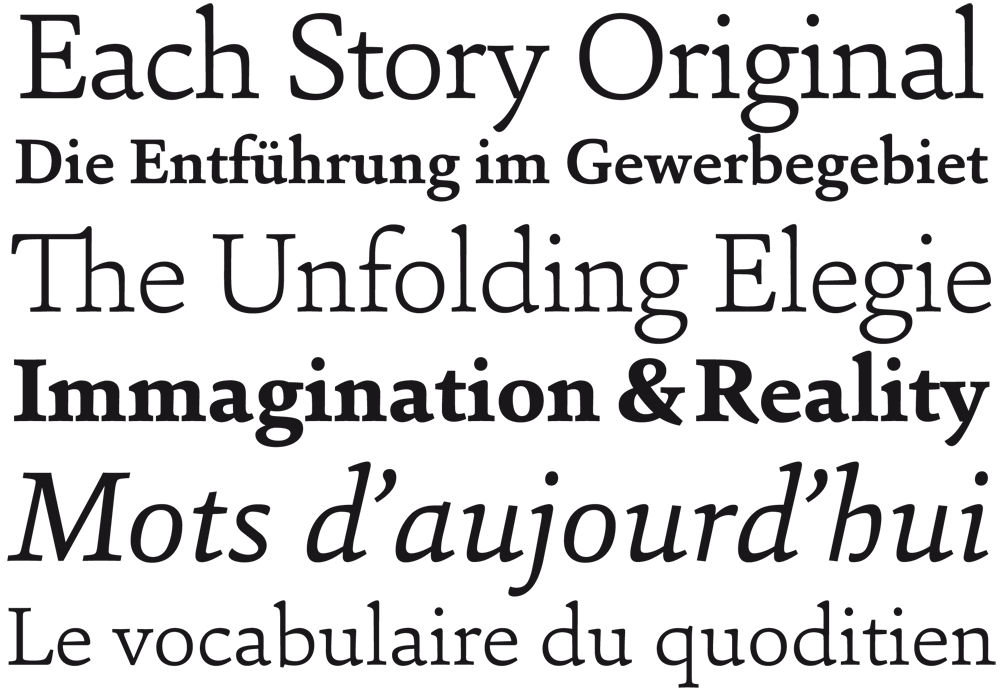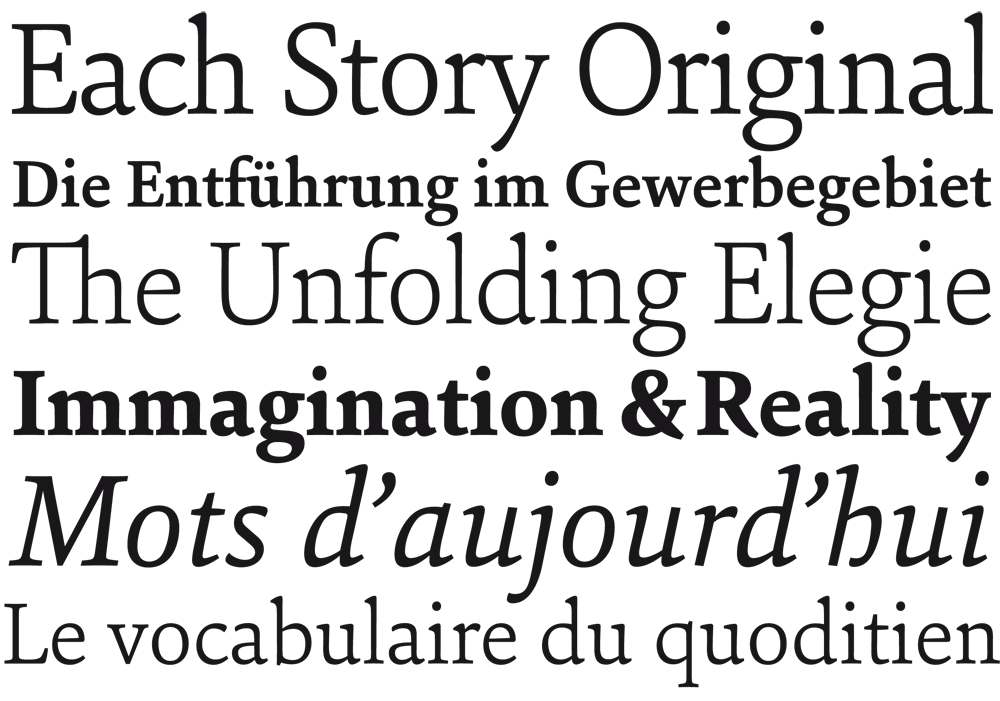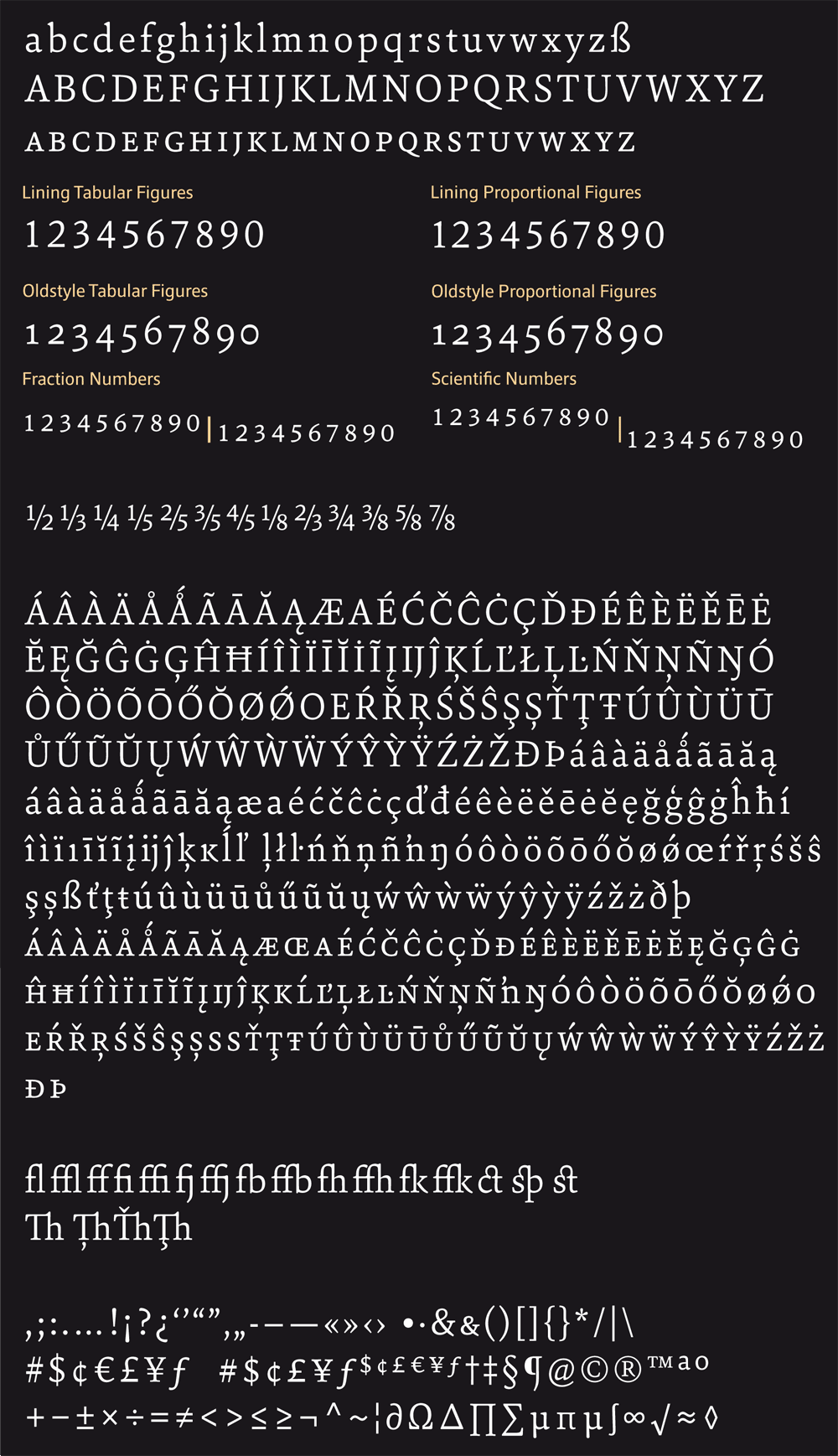
Sina ist eine starke, stabile … ja selbstbewusste Serif-Familie, entworfen von Dieter Hofrichter. Ausgeprägte Ober- und Unterlängen gepaart mit klassischen Proportionen sorgen für einen hohen Lesekomfort. Die Schrift knüpft an Qualitätsmerkmale des Bleisatzes an – Robustheit und Wärme –, besticht aber durch einen zeitgemäßen Anstrich. Mit ihrer feinen Strichstärkenabstufung von Extra Light bis Extra Bold eignet sich Sina OT für die wichtigsten typografischen Herausforderungen, vom Mengensatz über das Editorial Design bis hin zum Corporate-Einsatz.
Sina Nova ist die schmale Schwester von Sina OT, sie allerdings »Condensed« zu taufen ginge etwas zu weit. Sie hat eine leicht vertikale Betonung, eine größere Mittellänge lässt sie im Kleingedruckten größer wirken. Im Headline-Bereich erlauben ihre ökonomischen Proportionen mehr Text pro cm.
Beide Sina-Familien bestehen aus 12 Fonts, das sind sechs Strichstärken (von Extra Light bis Extra Bold) sowie die dazugehörigen Kursive. Alle Zeichensätze enthalten Standard- und bedingte Ligaturen, Kapitälchen, verschiedene Ziffernsätze mit de dazu passenden Währungszeichen, Brüche und wissenschaftliche Ziffern; Sprachausbau: Western European, Central und Eastern European.